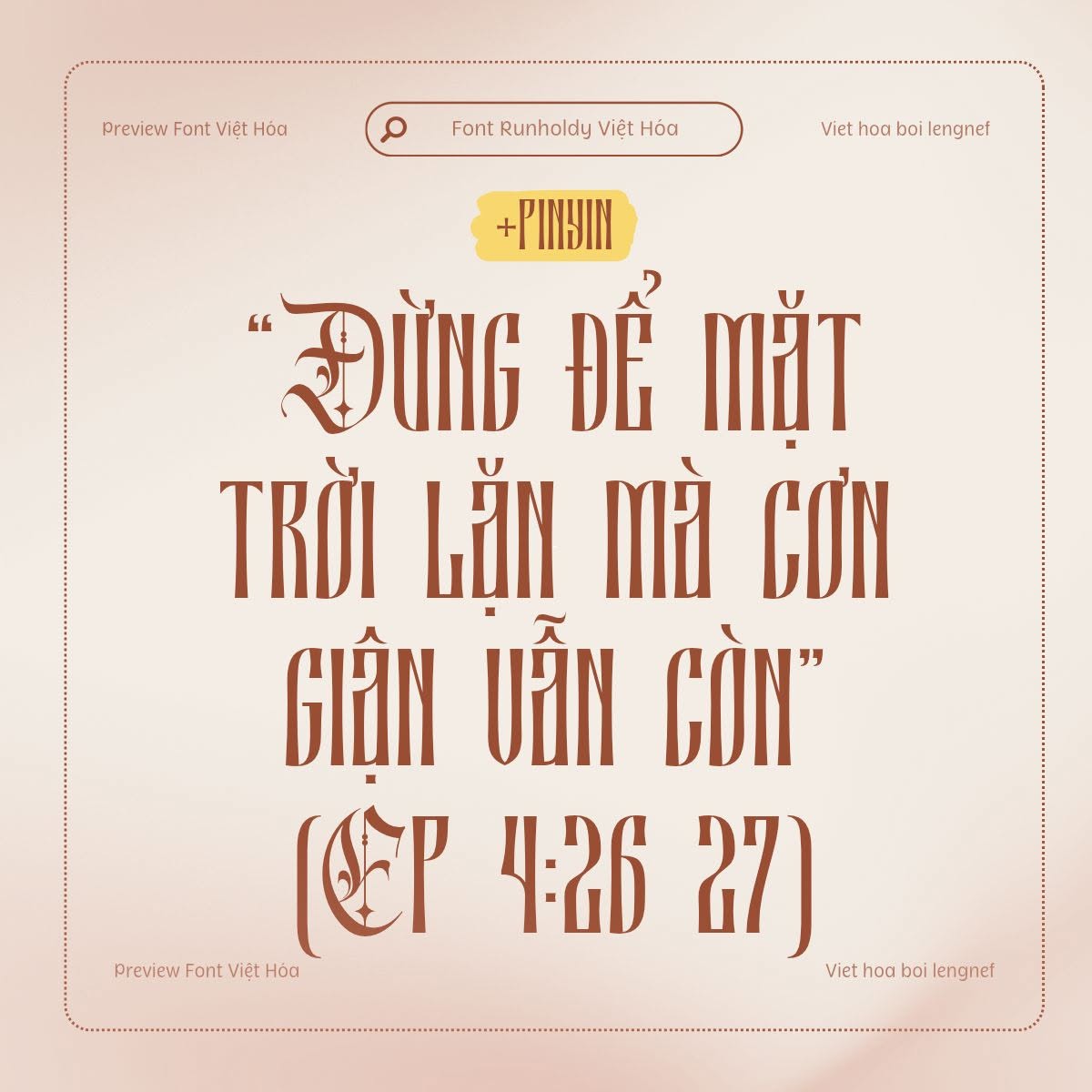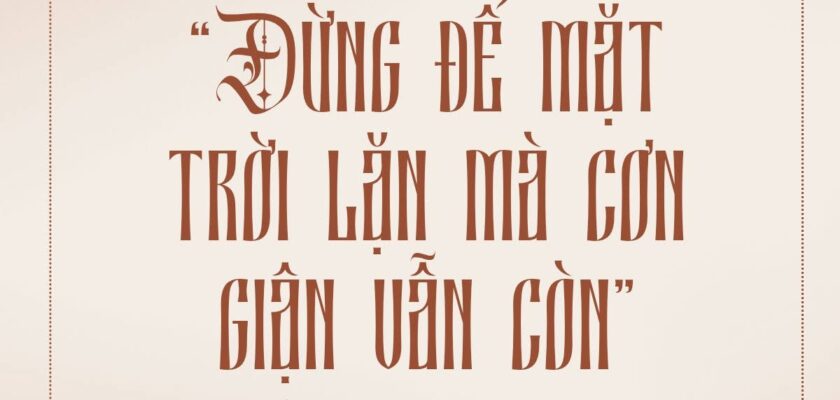
Share Font 84 || LF Runholdy
- Tác giả: Alit Design
- Việt hóa: lengnef
Runholdy là một kiểu chữ blackletter mới lạ được tạo bởi Alit Design, là một phông chữ độc đáo được thiết kế dựa trên ý tưởng về vẻ đẹp bí ẩn và phong cách hiện đại. Kết hợp các yếu tố của cả kiểu chữ sans serif hiện đại và blackletter, tạo nên một diện mạo nổi bật và khác biệt. Phù hợp với nhiều thiết kế mang tính trang trọng, mạnh mẽ, hiện đại…